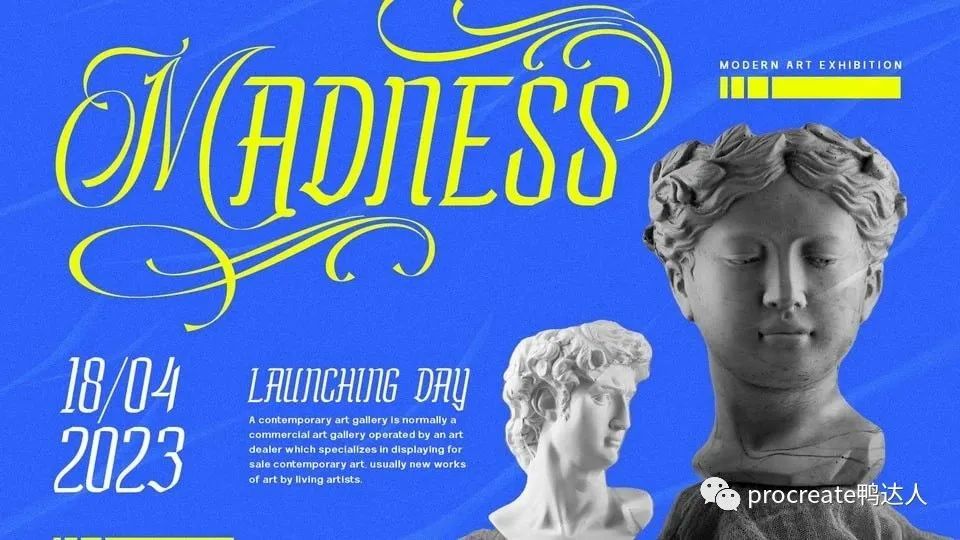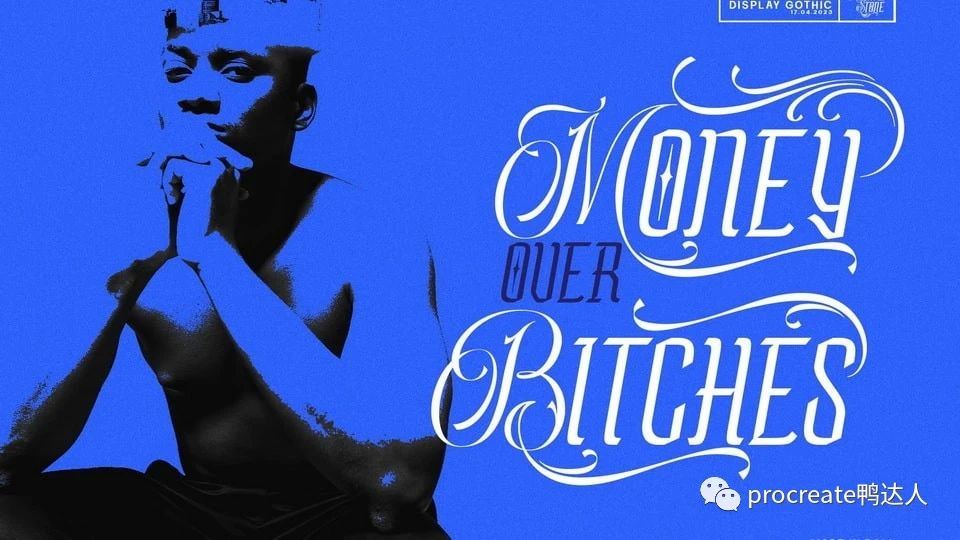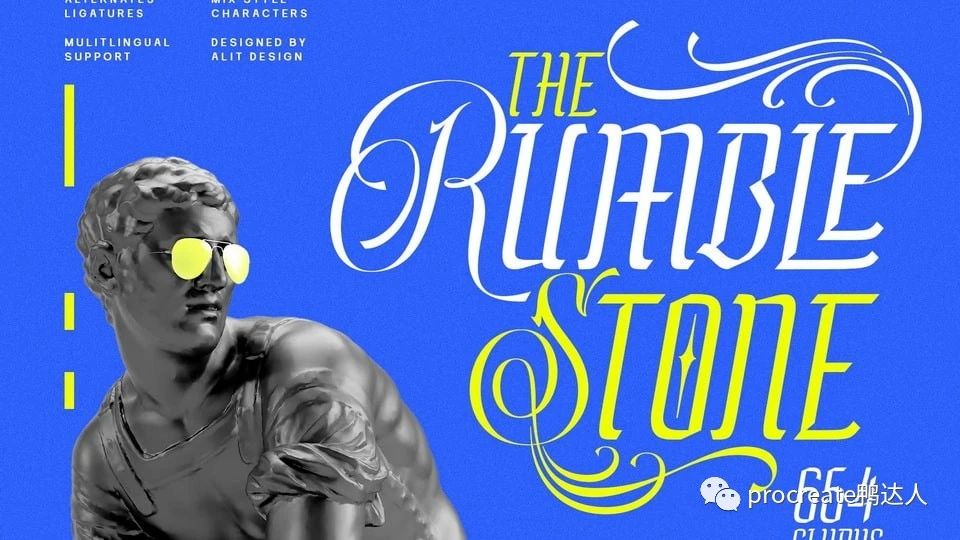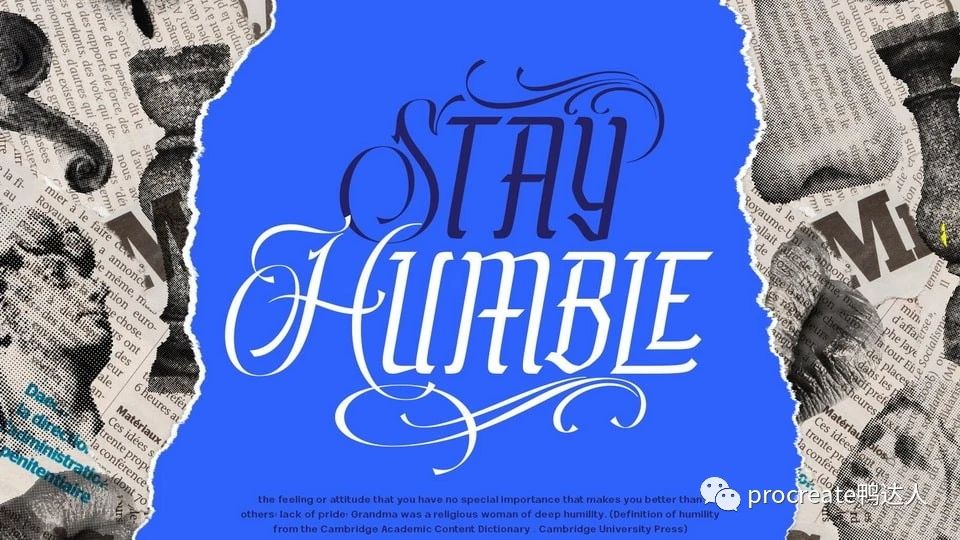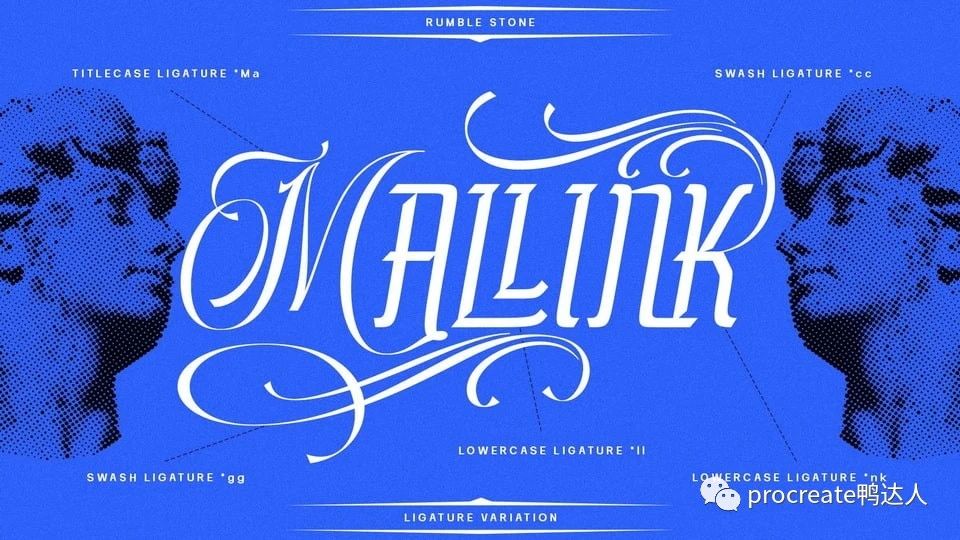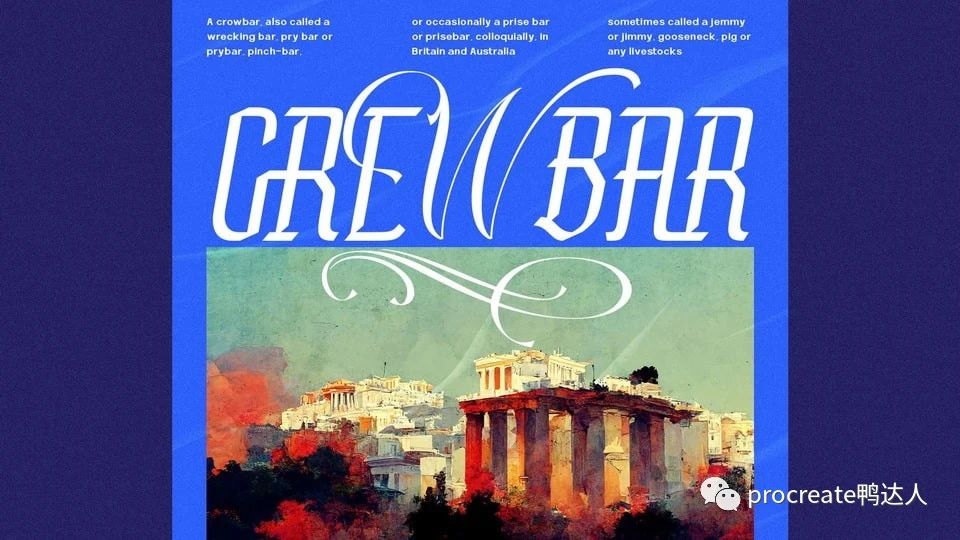
Rumble Stone是一款复古经典的英文花体装饰字体,共有654个字符,包括花标、特殊连字和替代字符,非常适合纹身设计和服装。该字体旨在支持 PUA unicode 并且是多语言的,允许它用于不同语言的各种项目。其独特而大胆的外观使其成为需要强烈和前卫外观的设计的绝佳选择。总的来说,“Rumble Stone”字体是一种多功能且富有表现力的字体,可以为其所用的任何项目增添个性和个性。